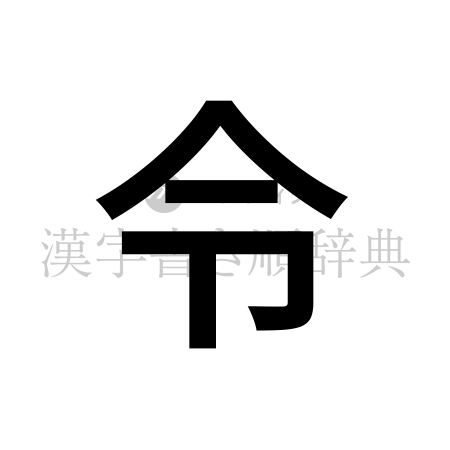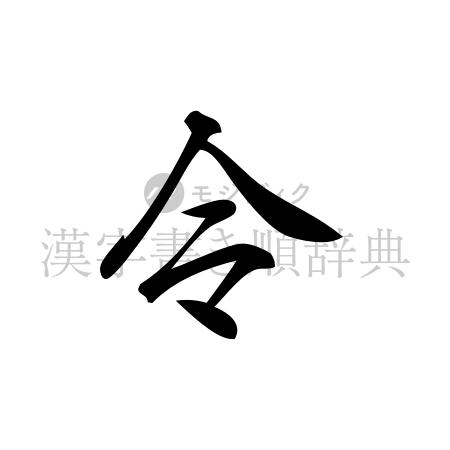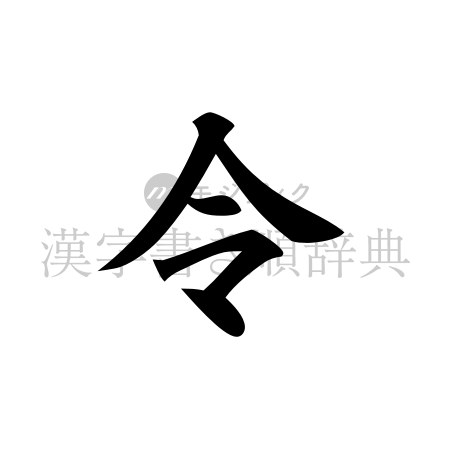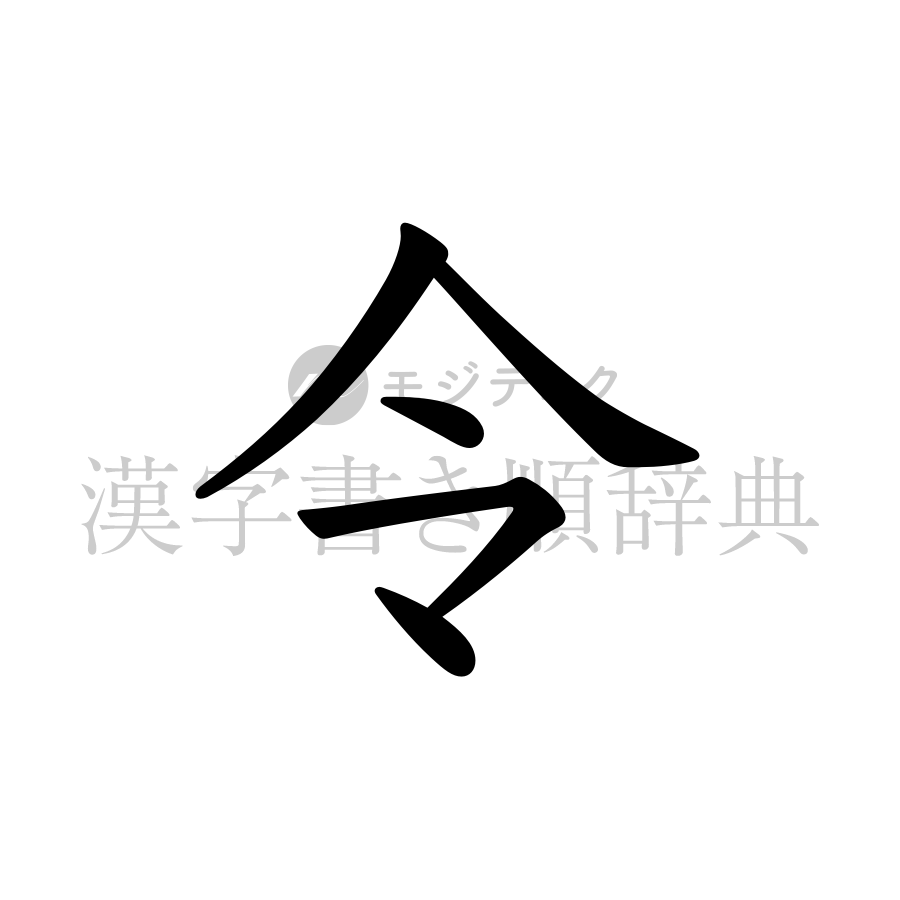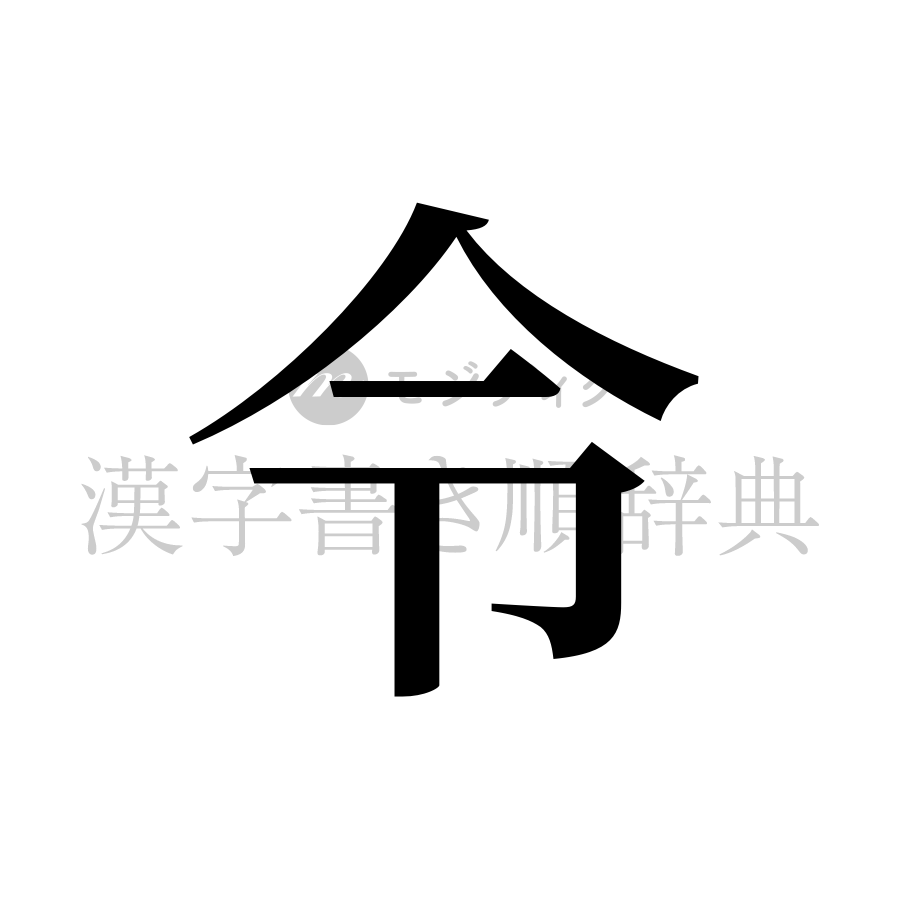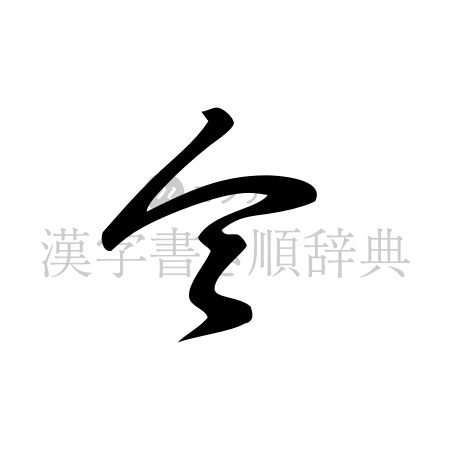
漢字「令」(レイ)の書き順・読み方・意味・部首・画数
「令」の書き順動画アニメーション(5画)
「令」の複数の字形・書き方について
漢字「令」は大きく分けると2通りの書き方があります。文化庁によると、どちらの字形も同じ「令」であり、どちらを使っても問題ありません。
「卩」の形
主に印刷物で使われる明朝体の「令」は新聞やパソコンのフォントなどで見られます。
「マ」の形
手書き(教科書体・楷書体)の「令」です。小学校で習う教科書体はこの形が標準です。
「令」の意味
- 命令する。
- 指示する。
- 法律や規則。
- 年齢。
- 良い、立派な。
- 季節の変わり目。
- 神のお告げ。
- 敬うべきもの。
「令」の意味の英訳
漢字は1文字で多様な意味を持ちますが、「令」を英語で表す場合、一般的には orders, laws, command, decree, good などがあります。
「令」の成り立ち・由来
| 構造 | 人が集まる場所を示す「亼」と、ひざまずく人の形「卩」とを合わせた字 |
「令」は会意文字です。上部の「亼」は人々が集まる場所や屋根の下を表し、下部はひざまずく人の姿をかたどっています。両者を合わせて、身分の高い者のもとに人がひざまずき、上からの言いつけを受ける様子を示しました。ここから「命令する」「指示する」の意味が生まれ、さらに定められた決まりとしての「法律・規則」、また敬われるべき立派なものという意から「良い・立派な」の意へと広がりました。神のお告げや季節の変わり目を指す用法もここに連なります。